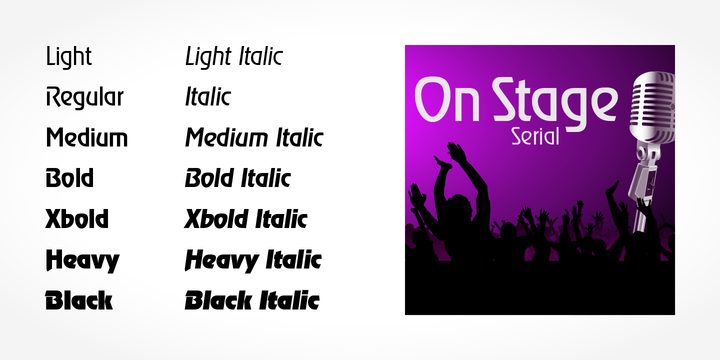
Suche Schriftart oder ähnlich "Benediktiner"
ich bin auf der Suche nach der Schriftart des "Benediktiner" Bieres.
Oder zumindest eine sehr sehr ähnliche (vor allem das "B" ist ja sehr markant).
die Kleinbuchstaben sollten aus der Revue sein:
Typeface:	Revue
Designer:	Colin Brignall
Year:		1968, 1987
Originally designed by Colin Brignall for Letraset in 1968.
Die Großbuchstaben sind wohl daraus mundgemalt und handgeblasen im Stil einer Kaiserzeit-Gotischen.
es ist aber nicht die Original Revue. Es gibt davon leichtere Schnittchen. Die fand man z.B. als Revel auf der WSI-Font-Collection. Etwa in diese Richtung geht auch die "On Stage Serial" von Softmaker:
Damit ist die Abstammung in etwa klar. Die Revue trieb es mit einer Kaiserzeit-Gotisch ...